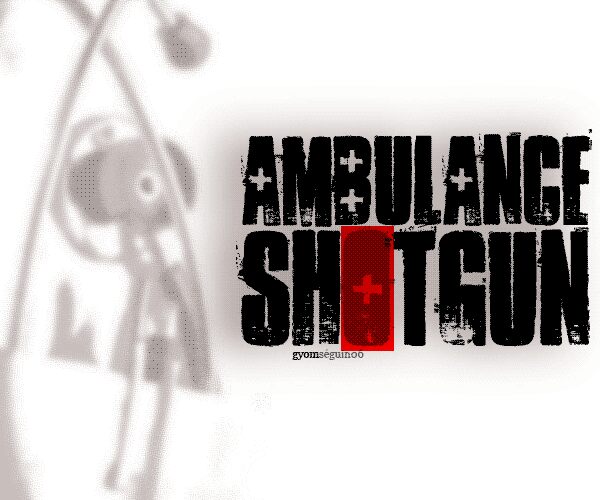
Ambulance Shotgun di GYOMSEGS è un font display gratuito ed eroso che sembra essere stato trascinato in una zona di guerra e timbrato con croci di primo soccorso. Le lettere nere e pesanti si sgretolano ai bordi in texture ruvide e punteggiate, mentre i segni più integrati in ogni glifo aggiungono un tocco brutale, un mix tra paramedico e punk. È rumoroso, angosciato e urgente: come una sirena resa in inchiostro e sporcizia.
Usa Ambulance Shotgun per dare una marcia in più a poster horror, titoli di giochi di zombie, copertine di album punk e metal, grafiche di protesta, loghi streetwear e banner social in stile grunge. Questo font gratuito dà il meglio di sé in grandi dimensioni, dove ogni schizzo e graffio risulta nitido. Per il testo di supporto, abbinalo a un carattere sans serif stretto e pulito per mantenere la leggibilità, lasciando che Ambulance Shotgun gestisca il caos.